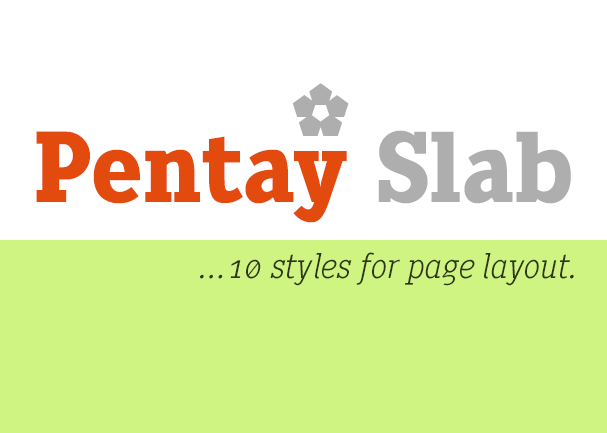
Pentay Slab Book Font
A Pentay é uma família de tipo Slab Serif desenvolvida para atender a necessidade dos designers de jornalismo e publicações de todos os tipos. Esta fonte foi projetada com cuidado, levando em consideração os parâmetros da letra, métrica e kérning para garantir que possuam máxima legibilidade. O conjunto completo de alternativas minúsculas e as avançadas características do OpenType estão incluídas na Pentay. Essas qualidades permitem uma utilização multifacetada, apropriada tanto para o design editorial quanto para publicações profissionais. Em um mundo onde a legibilidade e a qualidade visual podem fazer ou desfazer a comunicação de informações, é difícil encontrar uma fonte mais versátil do que a Pentay. A Pentay é uma excelente escolha para designers gráficos que buscam estabilidade, força e personalidade em um tipo.